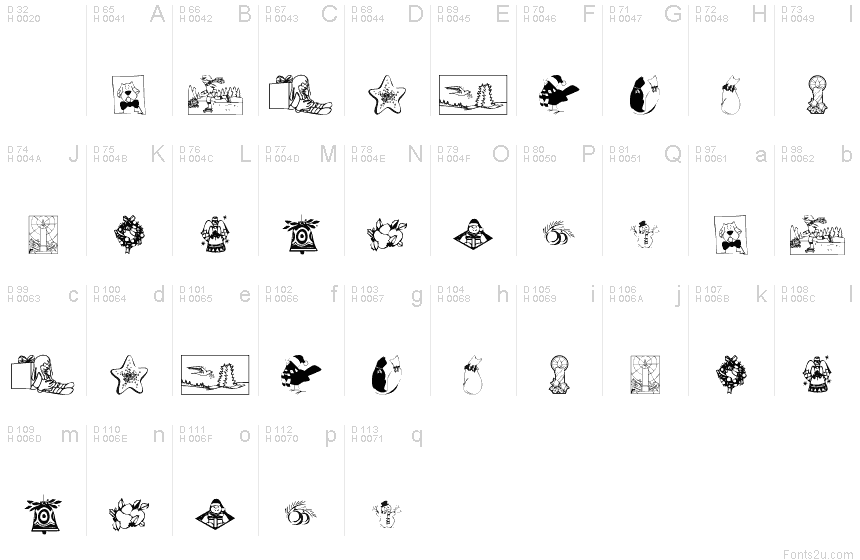
KR Christmas 2002 Dings 5 autorstwa Kat Rakos to bezpłatny, dekoracyjny font z ikonami. Ręcznie rysowane świąteczne motywy – wieńce z dużymi kokardami, stosy prezentów, przytulne zabawki i psotny kot z ostrokrzewem – wyglądają jak szkice na marginesie świątecznej kartki. Dzięki czystym, ale przyjaznym liniom, kształty te naturalnie wtapiają się w każdy projekt, nie wyglądając przy tym sztywno ani jak tanie clip-arty.
Użyj KR Christmas 2002 Dings 5, aby dodać świątecznego uroku kartkom okolicznościowym, etykietom na prezenty, materiałom edukacyjnym, zaproszeniom, stronom do scrapbookingu, naklejkom czy postom w mediach społecznościowych. Ikony świetnie sprawdzają się w małych rozmiarach, a powiększone zyskują jeszcze więcej uroku jako samodzielne ilustracje. Ten bezpłatny krój pisma idealnie łączy się z prostym, zaokrąglonym bezszeryfowym fontem, pozwalając grafikom opowiadać historię, podczas gdy tekst pozostaje czytelny i przejrzysty.